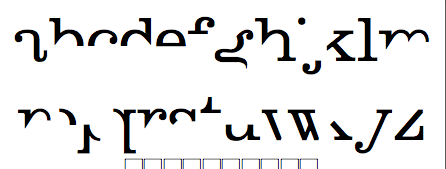
TypExperimente – Schriftgestaltung am Rande der Lesbarkeit
ich sitze zur zeit an meiner Bachelor-Arbeit: es geht um experimentelle Schriftgestaltung.
Die durch die Kombination und extreme Hervorhebung formaler Grundelemente (wie Serifenform, Strichstärke, Grauwert, Proportion etc.) mit emotionalen Parametern (elegant, seriös, leicht, standfest etc.) will ich Schrift-Experimente schaffen, die sich am Rande (aber noch im Rahmen) der Lesbarkeit bewegen.
Die Umsetzung soll folgendermaßen verlaufen:
Experiment #1 =
Parameter; formale und emotionale (fragmentartige Formen (1-D) + Serifen (5-C) + Haarlinie (3-A) + modisch)
+ Hypothese (»auch mit weniger als 60% der notwendigen Formen lässt sich der Text lesen«)
=> neuer Schriftentwurf oder bewiesene Unmöglichkeit
Durch ungewöhnliche oder schwer umsetzbare Kombinationen sollen interessante Schriftentwürfe und/oder gescribbelte Ansätze entstehen.
Die Schriften sollen sich aber dennoch nach typografischen Konventionen richten und keine »Free-Fonts à la dafont. com« werden.
Hier schon mal die formalen Grundelemente:
In den nächsten Wochen werde ich hier die ersten Entwürfe posten.
Ich freue mich über jedes Kommentar, jede noch so abstruse Parameter-Kombination, jeden link-Tipp etc.
ohne zu lange drüber nachgedacht zu haben:
unter 6 (Stil) fehlt "klassizistisch" bzw. "statisch", und vielleicht auch "gothic" im sinne amerikanischer Grotesk-Schriften.
Wobei sich die Kategorie der Punzenform mit der Kategorie Stil überschneidet, nicht?
Ich möchte bemerken, dass Schriftentwurf nicht Typografie ist. Nicht um rumzupingeln. Wenn wir das gleiche sagen, aber verschiedene Dinge meinen, schadet´s der Verständigung.
die ff canyou kennst du? ein bild finde ich so schnell nicht.
@Sebastian: mit "Stil" meinte ich weniger die Klassifikation, mehr den Stil des Strichs. "klassizistisch" würde sich dann aus "Kontrast:betont" (2-D) + "Stil:geometrisch" (6-A) – müsste da evtl. ein andres Wort für "Stil" benutzen.
Die "Punzen" sind vom "Stil" getrennt, damit z.B. auch eine "geschlossene Gebrochene" und eine "offene Gerochene" entstehen können.
Ein doppelschleifiges "gothic"-g ist allerdings noch nicht in der Matrix…
@Oleka: Schriftentwurf nicht Typografie = stimmt! müsste den thread-titel ändern.
@Christian: die "FF Canyou" kenne ich nicht – Bild finde ich leider auch keines
das hier hab ich finden können von der canyou:
zur Zeit versuche sich eine Ultra-Bold zu gestalten:
• kaum Weißraum – Zeilen verschwimmen zu einem schwarzen Block, Punzen und Buchstabenzwischenräume sind kaum von einander zu trennen
• betonte Serifen
• trotz Schwere noch etwas Dynamik
• humanistischer als z.b. die (grandiose) »
Klimax«
(sind PhotoBooth-Bilder –> ordentliche Scans kommen bald!)
Genau so was will ich auch machen -> einen Light-Schnitt derart fragmentieren, dass er kaum (aber dennoch) lesbar ist bzw. bei jedem Zeichen die zur Erkennbarkeit wichtigsten Form-Stücke herrausfinden.
Hat zwar weniger mit der Lesbarkeit zu tun aber ich finde das ist ein tolles Baukastensystem um verschiedene Stile zu vermischen. Vieleicht regt das irgendwie an.
Dein Thema find ich echt interessant. Hoffe man liest hier bald mehr davon.
Hi Jakob
könnte mir vorstellen dass das ganze auch in Richtungen geht die man eher als braver Typophiler meidet ...
z.B. verdrehter Wechselzug, links geneigte Kursive, böse Verzehrungen
Auch Zurichtung und Durchschuß könnte ich mir noch als Ebene vorstellen.
Oder: keine einheitliche Grund- x- Versallinie
*seuftz* echt cooles Thema...
@Plubird: was mit umgekehrten Wechselzug zu machen, oder die Grundlinie etc. zu ignorieren, das ist eine sau gute Idee. Danke!
eine linksgeneigete kursive gibt's leider schon^
Im Moment bastle ich gerade an:
• 1) einer Ultra-bold-maximaler-Schwarzwert-Schrift mit leichter Dynamik.
2) einer fragmenthaften Schrift mit minimalen Formstücken, auf Grundlage des Artikels, den Ralf empfohlen hat. Evtl. werde ich da auch zwei Schnitte machen: einen voll-formigen Light-Schnitt und einen Schnitt mit leichtem Kontrast und den notwendigen Formstücken – so kann ich dann »History«-modular-artig an einen langweiligen Light-Schnitt die wichtigen Merkmale für die Lesbarkeit betonen.
3) »You have got the balls – drop it hard!«, ein nicht ganz korrekter Zusammenschnitt von Snoop-Dog-Lyrics und einem Idiom: Es geht auf jeden Fall um eine Schrift mit Tropfenserifen, oder besser gesagt um Tropenserifen mit Buchstaben dran.
4) einer »Capitalis Extremis« mit extrem, unausgeglichenen Proportionen
1. da bin ich manchmal ein bisschen pissig- so eine kopflastige bachelorarbeit in der typo öffentlichkeit aus zu tragen, find ich neben der spur. sind wir alle jetzt dein betreuer? hast du keinen prof?
Das Thema in der Typo-Öffentlichkeit aus zu tragen, find ich die richtige Spur: Ich verlange von niemanden, dass er mir meine Arbeit abnimmt. Und wen das Thema nicht interessiert, muss auch nichts schreiben.
Da mir hier bisher einige Tipps gegeben und gute Artikel empfohlen wurden, die ich an meiner FH nicht bekommen habe, nutze ich die Nahrungsmittelergänzung und freue ich mich weiterhin über jeden, der spontan irgendein Einwand oder ein »ah, da fällt mir was in der Richtung ein« parat hat.